Artikel ini menyajikan 60 font tulisan tangan yang keren dan gratis untuk desain poster dan logo.
Font bergaya tulis tangan (handwritten font) kini banyak digunakan untuk berbagai desain.
Tampilannya yang seperti ditulis tangan memberi kesan kasual, santai, tidak terlalu formal; namun juga kelihatan gaul, menyenangkan, ramah, dan indah.
Selain untuk judul poster dan logo, font tulis tangan juga cocok untuk desain berupa:
- Brosur
- Undangan
- Packaging
- Kartu ucapan
- Judul ppt
- Judul banner
- Judul video
- Judul catatan aesthetic
- Judul buku atau judul novel
- Quotes atau kutipan motivasi
- Caption Instagram post dan Instagram story
- Header dan postingan Twitter, Facebook, atau toko online, dan masih banyak lagi
Silakan scroll ke bawah untuk melihat pilihan font tulisan tangan, baik yang bergaya cetak tebal (bold style), goresan kuas (brush font), gaya kapur tulis (chalk font), font dengan huruf besar atau huruf kapital semuanya, serta font tulis tangan yang lucu.
Font Besty
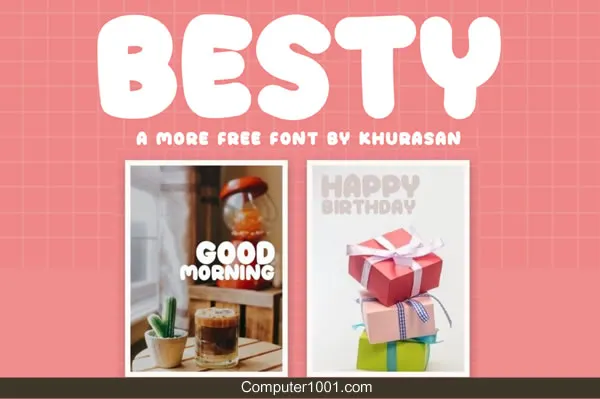
Font tebal keren untuk desain Anda.
Font Big Snow
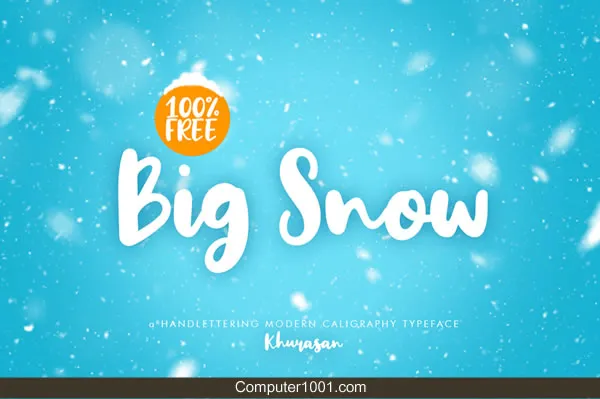
Font Binjay
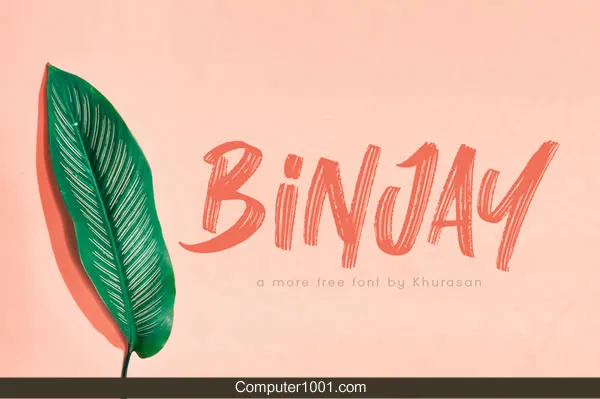
Font Binjay memiliki bentuk seperti goresan kuas.
Font Bluenesia
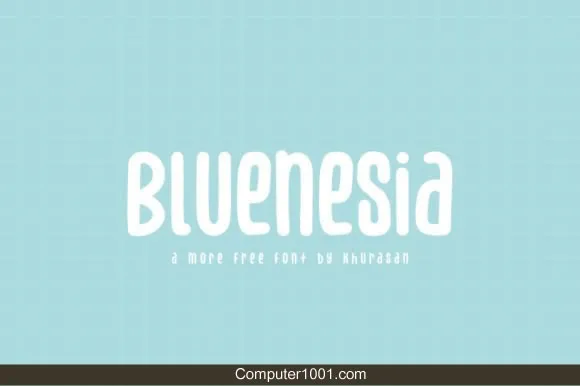
Karakter font Bluenesia memiliki bentuk yang kurus dengan ketinggian yang sama. Font seperti ini sangat menghemat tempat. Cocok untuk desain yang ukurannya kecil tapi perlu banyak tulisan.
Font Blueto
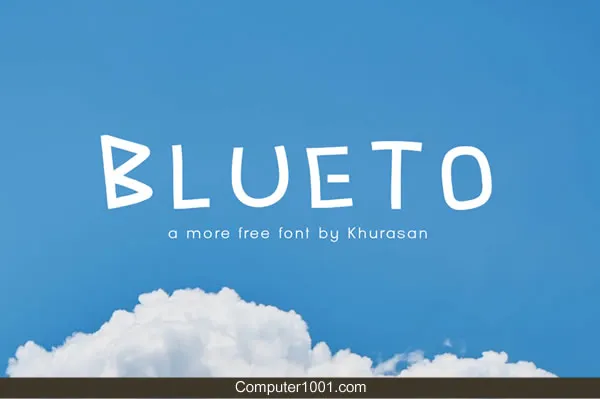
Font Blueto memiliki huruf besar semuanya, kecuali huruf k dan y. Huruf A, B, D, P, dan R memiliki bentuk runcing yang akan membuat desain Anda makin kelihatan makin unik dan spesial.
Font Cardenio Modern
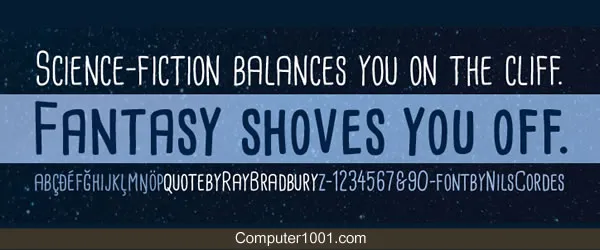
Font tinggi ramping dengan huruf kapital semuanya. Juga memiliki angka 0 – 9 dan huruf aksen. Cocok untuk kutipan, catatan, dan apa pun yang layak untuk dikatakan. Memiliki 2 ketebalan font (reguler dan bold).
Font Cintaly
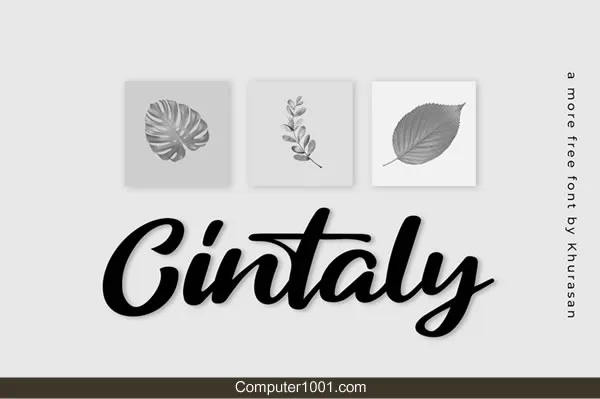
Cintaly adalah font tebal aesthetic.
Font Cute Written
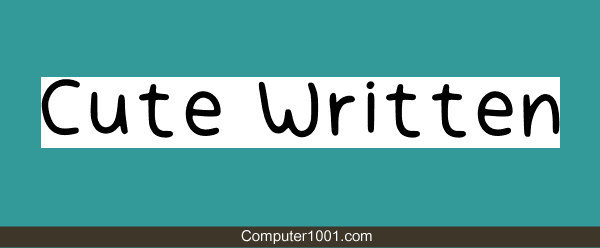
Font Cute Written memiliki bentuk yang lebar dengan huruf a-z kapital dan kecil serta tanda baca. Font ini tidak memiliki angka.
Dalgona Candy Font
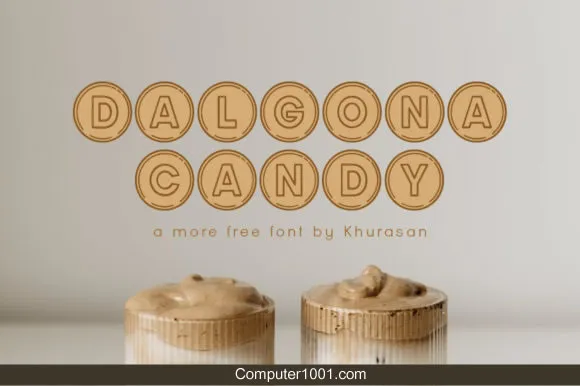
Dalgona Candy adalah font display yang keren dan modern. Cocok untuk poster, logo, majalah, sampul, spanduk, dan banyak lagi.
Semua huruf, angka, dan simbol berada di dalam lingkaran atau bulatan yang mirip dengan permen dalgona. Mungkin desainernya terinspirasi dari drama Korea Squid Game.
Font Dosen Killer
Font ini mirip ditulis dengan kapur.
Font Eatday
Ada tambahan garis di bawah karakter font Eatday, sehingga kelihatan seperti memiliki efek 3D.
Fegan Font
Fegan adalah font display dengan aksen garis. Tampilan autentiknya akan menambah kesan personal dan realistis pada desain Anda.
Font Flyover
Font Flyover adalah font tulis tangan yang elegan dengan huruf kecil yang bersambung.
Font Fonters
Font Foxbot
Font ini juga memiliki tampilan seperti goresan kuas.
Font Give Away
Font Give Away memiliki bentuk yang feminin seperti tulisan pada banner produk yang ditujukan untuk remaja perempuan, serta produk bayi dan ibu.
Font Handgoal
Font tebal dengan huruf a – z kapital semuanya.
Font Handletterink